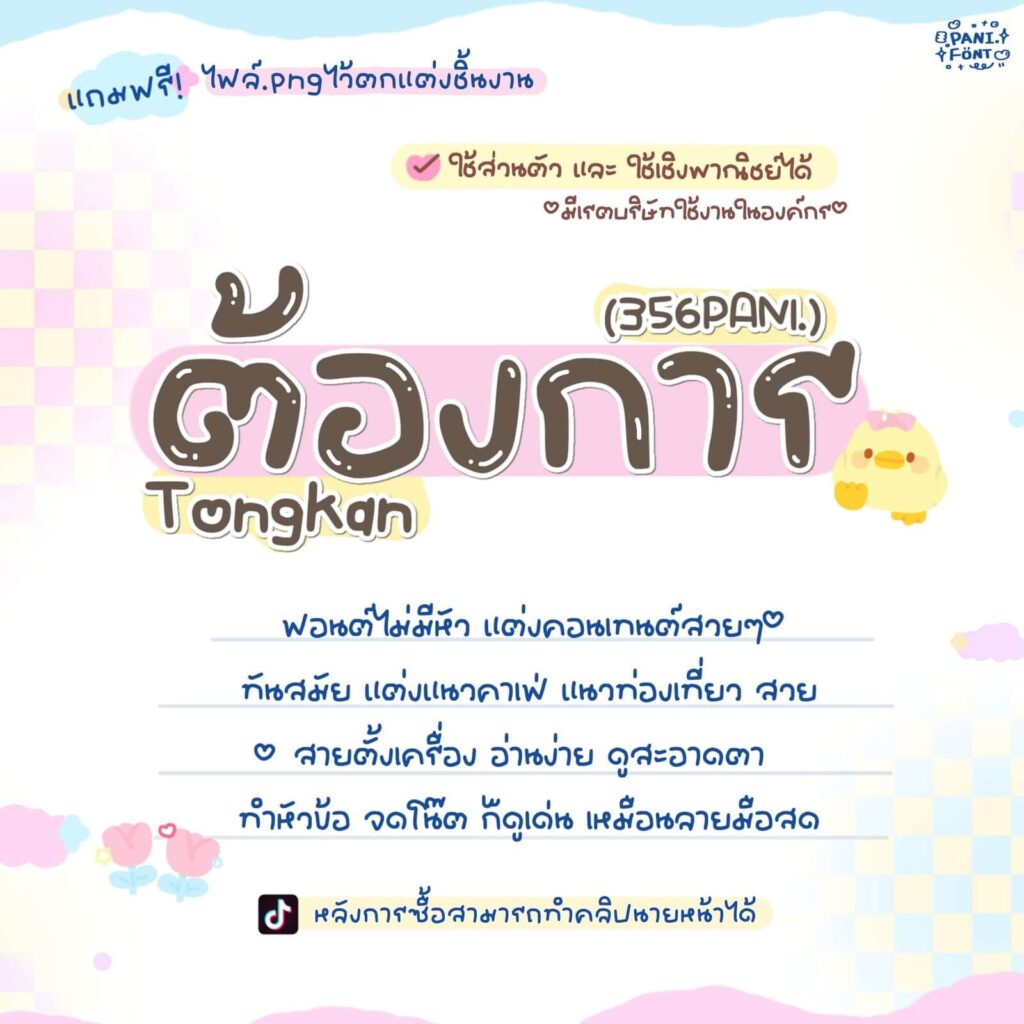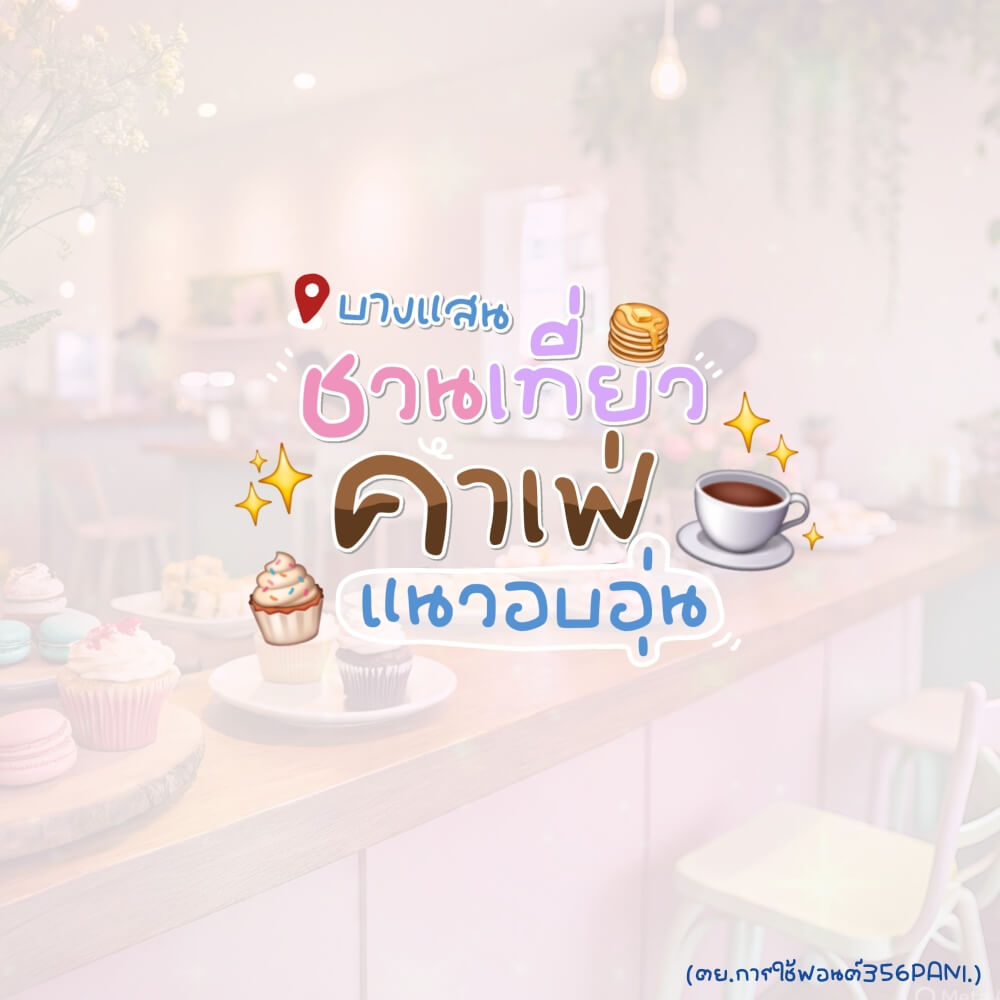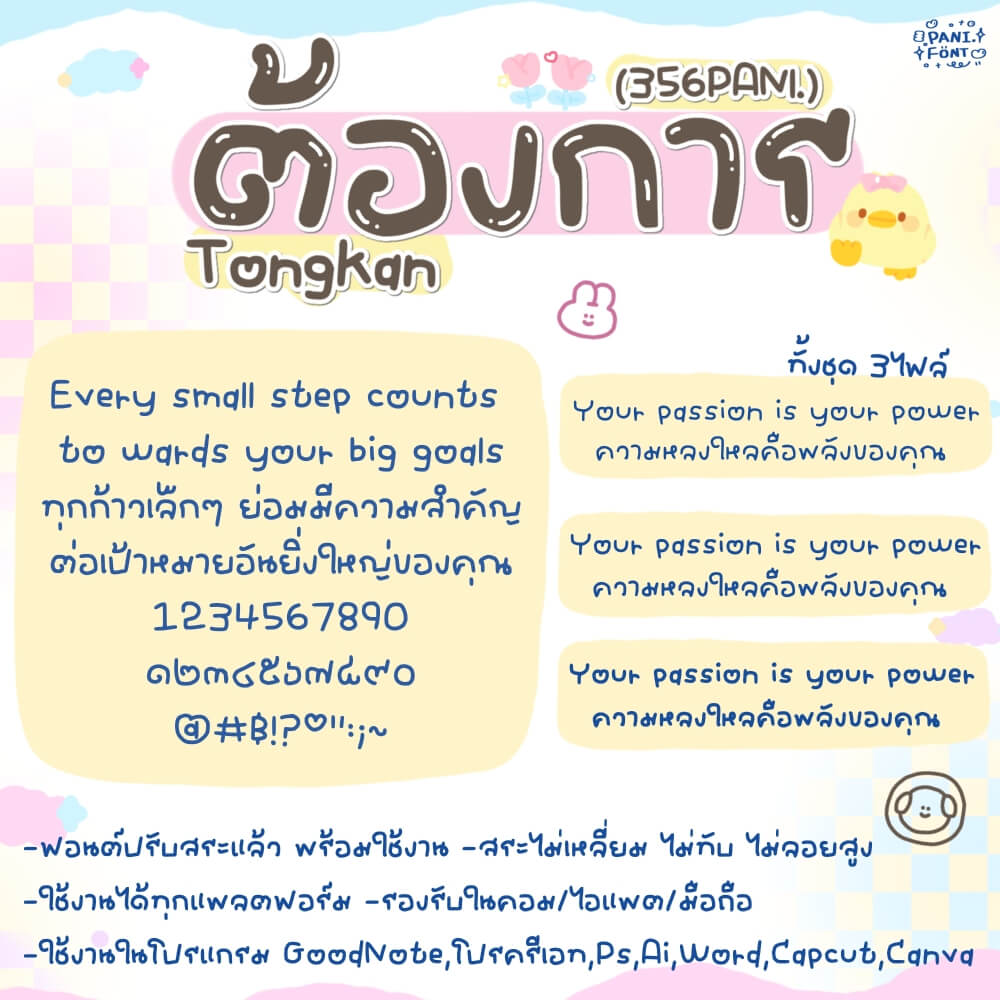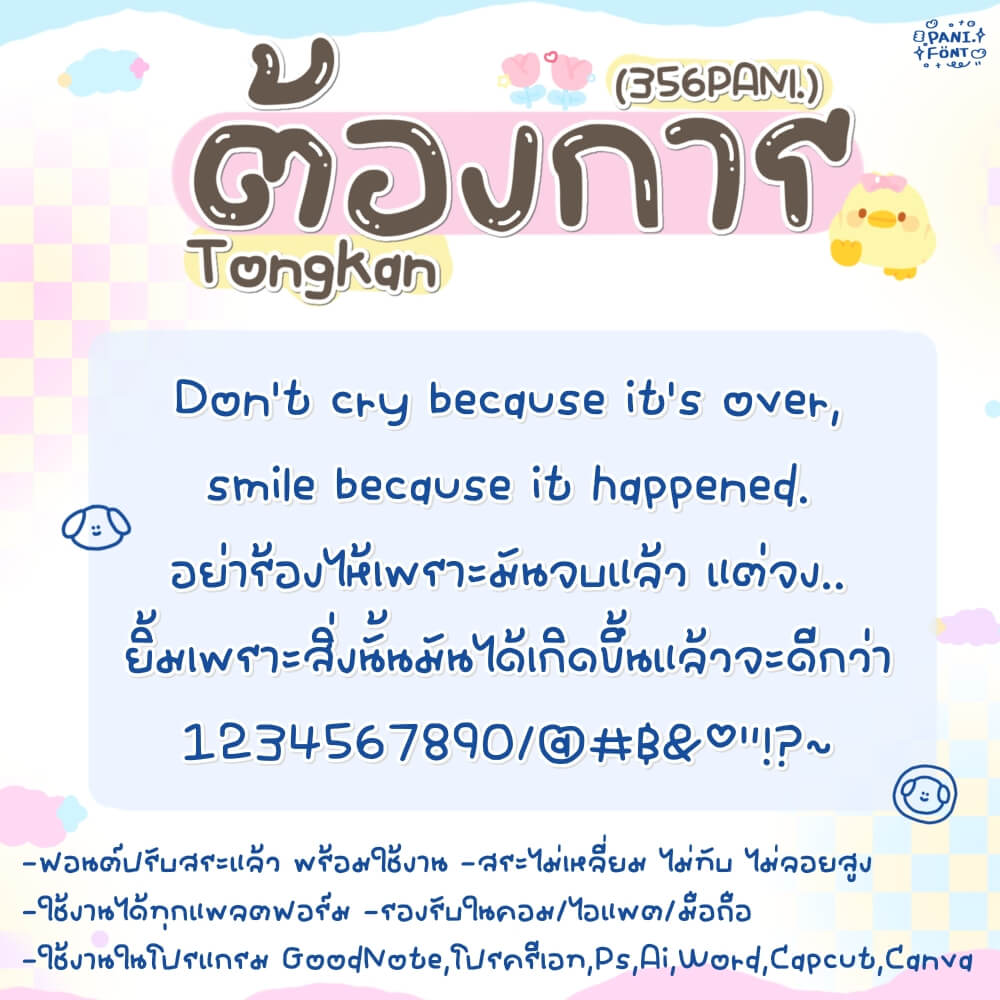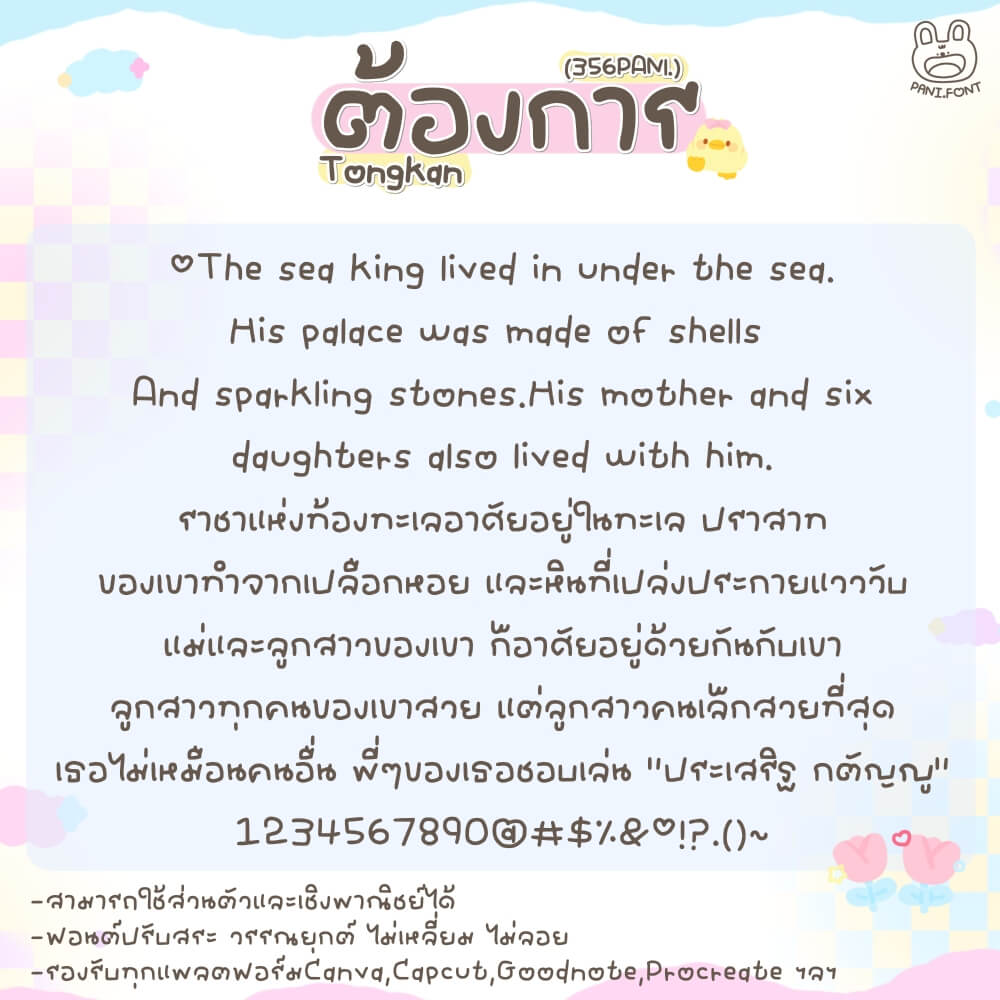
ฟอนต์ 356PANI.ต้องการ – ฟอนต์ไม่มีหัว แต่งคอนเทนต์สวยๆ ทันสมัย แต่งแนวคาเฟ่ แนวท่องเที่ยว สวยเลยค่ะ สายตั้งเป็นฟอนต์เครื่อง อ่านง่าย ดูสะอาดตา น่ารัก ฟีลจดโน้ตด้วยลายมือตัวเอง
356PANI.ต้องการ